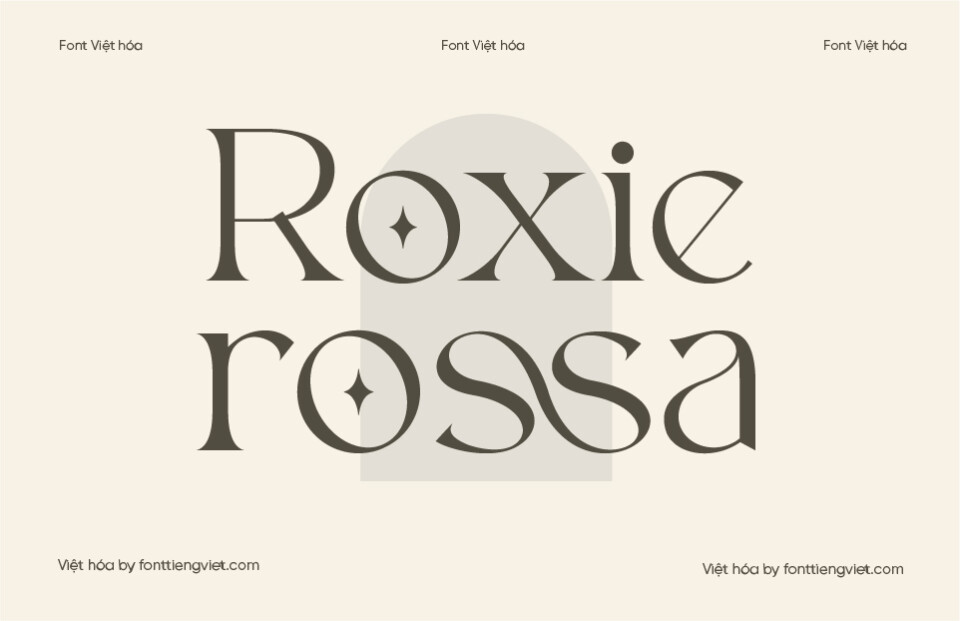
Font Việt hóa 1FTV VIP Roxie Rossa
Giới thiệu về Font Việt hóa 1FTV VIP Roxie Rossa
Trong thế giới thiết kế đồ họa hiện đại, việc tìm kiếm một bộ Font Miễn Phí chất lượng cao và phù hợp với tiếng Việt luôn là ưu tiên hàng đầu của các designer. Font Việt hóa 1FTV VIP Roxie Rossa xuất hiện như một giải pháp hoàn hảo, mang đến sự kết hợp tinh tế giữa nét cổ điển và hơi thở đương đại. Đây là một kiểu chữ thuộc phong cách Serif cách điệu, nổi bật với các đường nét thanh mảnh nhưng vô cùng sắc sảo, tạo nên cảm giác sang trọng và đẳng cấp cho mọi bản thiết kế. Việc sử dụng bộ font này không chỉ giúp nội dung trở nên dễ đọc mà còn nâng tầm thẩm mỹ cho các dự án từ in ấn đến kỹ thuật số.
Đặc điểm nổi bật của bộ chữ Roxie Rossa
Font Việt hóa 1FTV VIP Roxie Rossa sở hữu cấu trúc chữ độc đáo với những đường cong uốn lượn mềm mại tại các điểm nối. Điểm đặc biệt của phiên bản VIP này chính là bộ ký tự đi kèm (ligatures) và các chữ cái thay thế phong phú, cho phép người dùng sáng tạo ra những tiêu đề độc bản. Các dấu tiếng Việt được đội ngũ 1FTV tinh chỉnh tỉ mỉ, đảm bảo sự cân đối tuyệt đối và không bị lỗi hiển thị khi gõ văn bản dài. Nhờ vào độ tương phản cao giữa nét thanh và nét đậm, bộ chữ này cực kỳ thu hút thị giác ngay từ cái nhìn đầu tiên.
Ứng dụng thực tế của Font Việt hóa 1FTV VIP Roxie Rossa
Nhờ vẻ ngoài thanh lịch, Font Việt hóa 1FTV VIP Roxie Rossa thường xuyên được lựa chọn cho các thiết kế thương hiệu cao cấp. Bạn có thể dễ dàng bắt gặp kiểu chữ này trên bao bì mỹ phẩm, nhãn mác thời trang hoặc thực đơn của các nhà hàng sang trọng. Đối với lĩnh vực xuất bản, đây là lựa chọn tuyệt vời cho tiêu đề tạp chí, bìa sách nghệ thuật hoặc các đoạn trích dẫn truyền cảm hứng trên mạng xã hội như Instagram và Pinterest. Bên cạnh đó, các cặp đôi cũng rất ưa chuộng bộ font này để thiết kế thiệp cưới, tạo nên không gian lãng mạn và tinh tế cho ngày trọng đại.
Lưu ý khi sử dụng trong thiết kế chuyên nghiệp
Mặc dù Font Việt hóa 1FTV VIP Roxie Rossa rất đẹp, nhưng để đạt hiệu quả tối ưu, bạn nên kết hợp nó với các font Sans-serif đơn giản cho phần nội dung văn bản (body text). Điều này giúp tạo ra sự tương phản cần thiết và tránh gây rối mắt cho người xem. Hãy tận dụng tối đa các tính năng OpenType để kích hoạt các ký tự đặc biệt, giúp tác phẩm của bạn có chiều sâu nghệ thuật hơn. Ngoài ra, việc điều chỉnh khoảng cách giữa các chữ cái (kerning) cũng là một bước quan trọng để bộ font phát huy hết vẻ quý phái vốn có của mình trong các không gian trắng rộng lớn.
Kết luận về bộ Font Việt hóa 1FTV VIP Roxie Rossa